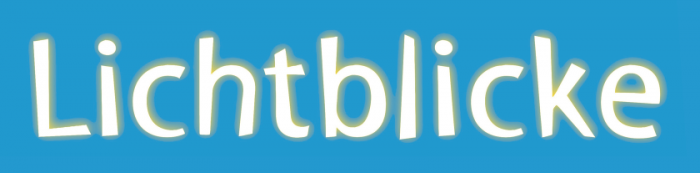
MultipleMaster-Font Myriad Tilt?
Ich kniffle gerade an der Suche nach einer alten Schrift und würde mich sehr freuen, wenn mir jemand von Euch weiterhelfen könnte!
Für einen Soft-Relaunch suche ich nach einem fetten und breiteren Schnitt der Myriad Tilt.
Ich bin mir recht sicher, dass es die früher als Multiple-Master-Font gab.
Doch nun als Opentype-Font gibt es sie nur mehr in einem Schnitt.
Hat eine/r von Euch eine Idee, wo ich einen alten MM-Schnitt herbekommen könnte?